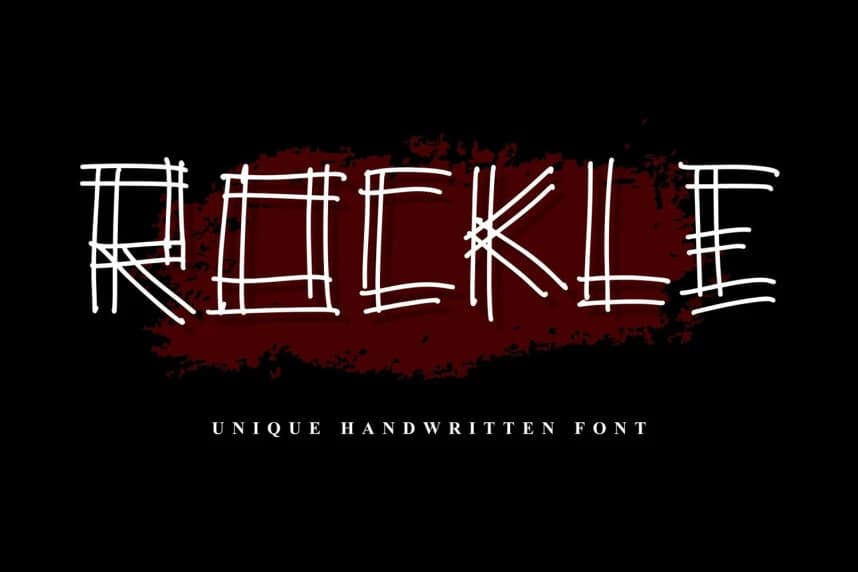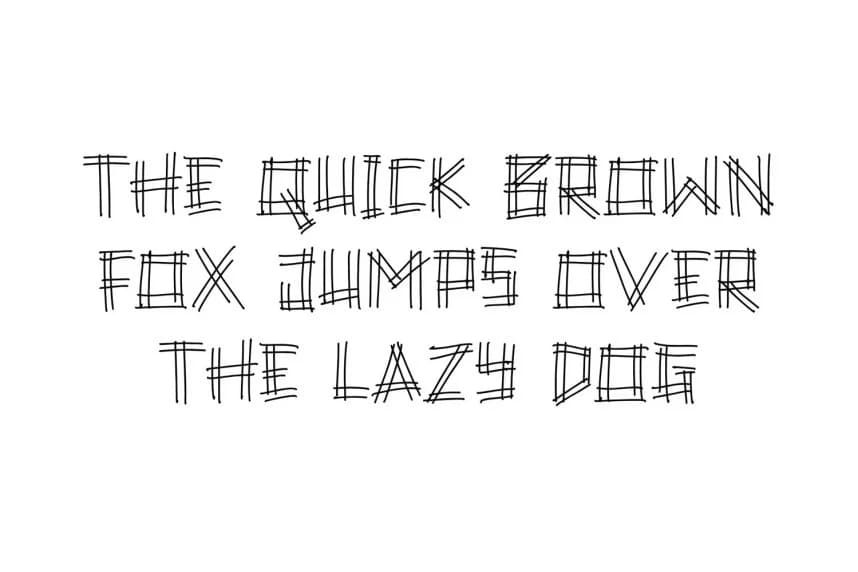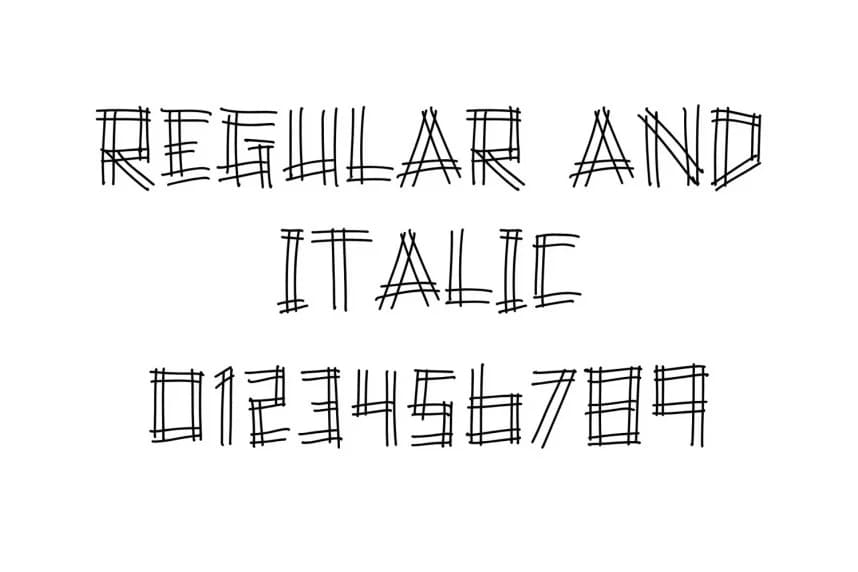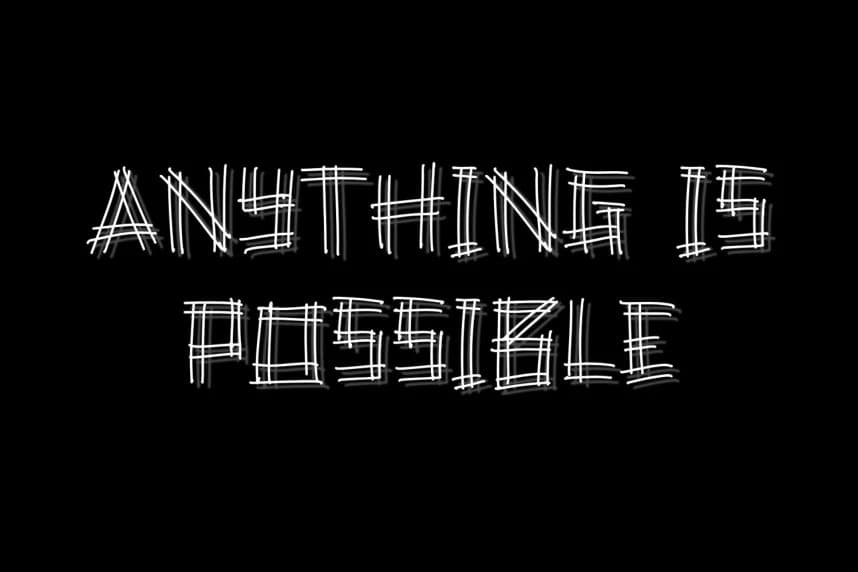
Rockle Font
ROCKLE Font, cesur ve ifade dolu bir el yazısı fontudur; ham, keskin ve sanatsal bir hava yakalar. Düzensiz çizgiler ve eskiz benzeri bir yapıya sahip olacak şekilde tasarlanan bu font, herhangi bir tasarımda öne çıkan benzersiz bir kişilik sunar.
ROCKLE Font, ham, sert ve sanatsal bir his veren cesur ve ifade gücü yüksek bir el yazısı fontudur. Düzensiz çizgiler ve eskiz benzeri bir yapıya sahip olarak tasarlanmıştır; bu font, herhangi bir tasarımda öne çıkan benzersiz bir kişilik kazandırır.